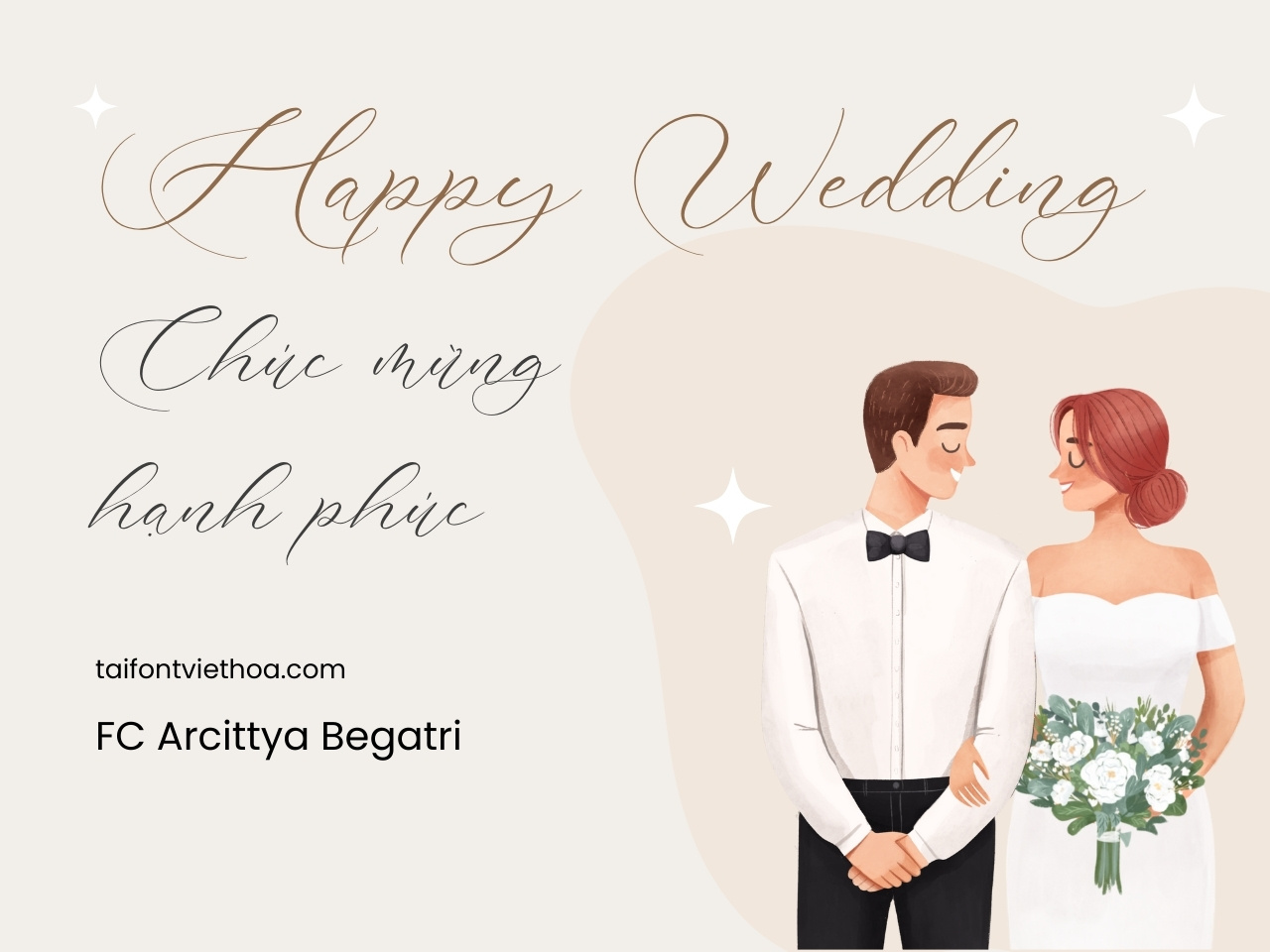
Font việt hóa FC Arcittya Begatri
Giới thiệu về font Arcittya Begatri và phiên bản Việt hóa
FC Arcittya Begatri là phiên bản Việt hóa từ font gốc “Arcittya Begatri” – một thiết kế thuộc nhóm font chữ ký (signature script) đầy quyến rũ đến từ studio CalligraphyFonts. Font được phát hành trên Creative Market, nổi bật với đường nét mềm mại, thanh thoát, mang hơi hướng thủ công và đậm chất cá nhân. Font gốc hỗ trợ hơn 60 ngôn ngữ quốc tế sử dụng hệ Latin, phù hợp với nhiều dự án thiết kế cần tạo dấu ấn riêng biệt.
Phiên bản Việt hóa FC Arcittya Begatri do cộng đồng Font Chuẩn thực hiện, đảm bảo đầy đủ bộ dấu tiếng Việt, tinh chỉnh tỷ lệ ký tự để giữ nguyên nét uyển chuyển và tính nghệ thuật vốn có của bản gốc. Toàn bộ font được tối ưu hóa để tương thích tốt trong các phần mềm đồ họa như Illustrator, Photoshop hoặc Canva. Font này đã được taifontviethoa.com sưu tầm, chọn lọc và áp dụng vào các dự án thiết kế thực tế trong lĩnh vực mỹ phẩm, thời trang, sự kiện cưới và branding cá nhân.
Đường nét nghệ thuật và ứng dụng phong phú
FC Arcittya Begatri mang đậm phong cách viết tay nghệ thuật với các nét chữ bay bổng, kết hợp ligature tinh tế và swash trang trí độc đáo. Cấu trúc chữ có độ nghiêng nhẹ, tạo cảm giác tự nhiên như được viết bằng bút lông, phù hợp để dùng làm chữ ký thương hiệu, tiêu đề nổi bật, hoặc nhấn mạnh thông điệp trong thiết kế đồ họa. Bộ ký tự hoa được trau chuốt, mang đậm dấu ấn cá nhân và cảm xúc.
Font này đặc biệt phù hợp trong các lĩnh vực như spa, mỹ phẩm, thiệp cưới, logo thương hiệu nữ tính, boutique, thời trang cao cấp và ấn phẩm nghệ thuật. Sự mềm mại và sang trọng của FC Arcittya Begatri khiến nó trở thành lựa chọn lý tưởng cho các dự án thiết kế cần truyền tải cảm xúc nhẹ nhàng nhưng vẫn giữ vẻ cao cấp và chuyên nghiệp.